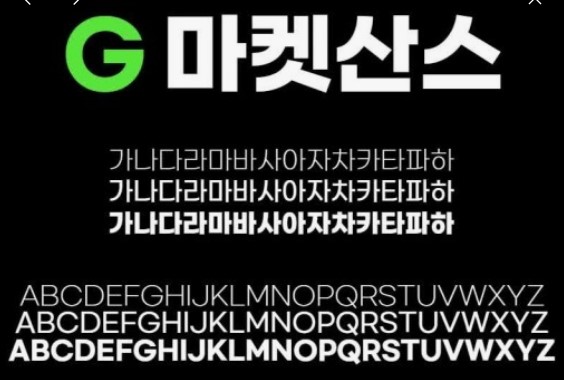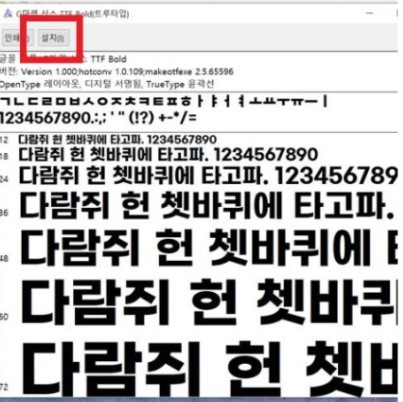
G마켓 산스 폰트는 지마켓에서 제공 하는 무료 폰트 입니다! 깔끔하고 가독성이 좋은 디자인으로 활용도가 높아 인기가 많은데요, 개인적인 용도 뿐만 아니라 상업적에도 많이 쓰여 사람들이 많이 찾습니다!
G마켓 (지마켓) 산스 폰트
G마켓 산스 폰트는 2023년도에 지마켓 에서 출시한 무료 상용 폰트 입니다. 깔끔하고 가독성이 높아 개인사용 뿐만 아니라 상업 용도로도 많은 사람들이 사용 합니다.
G마켓 산스 폰트는 매년 버전을 거듭하고 있습니다. 2023년에 출시한 가장 최신버전에서는 개선된 점이 몇가지가 있습니다.
- 한글 및 영문 글자 개선 : 가독성 향상을 위해 일부 모양을 수정 했습니다.
- 새로운 글꼴추가 : G마켓 산스 둥근이라는 글꼴을 추가 했습니다, 둥근 이미지로 더욱 부드러운 느낌을 줍니다
G마켓 산스 폰트 주요 특징📌
- 손으로 쓰는 듯한 자연스러운 필순 으로 깔끔한 느낌 제공